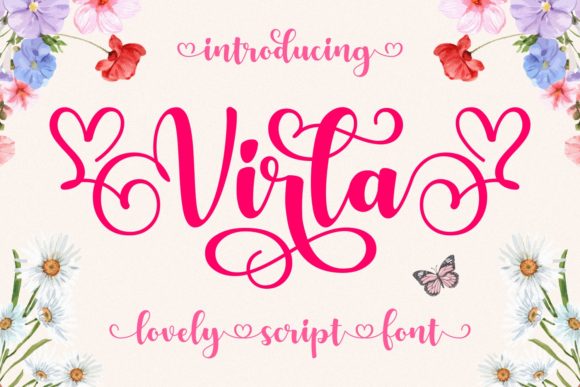
Вирла - это сладкий, круглый и гибкий рукописный шрифт.
Теплый, романтичный и весёлый, этот шрифт превратит каждую вашу идею проекта в настоящее произведение искусства. Весело проведите время с этим прекрасным шрифтом и изучите его бесконечные вариации. Этот шрифт закодирован в PUA, что означает, что вы можете с легкостью получить доступ ко всем глифам и следам!